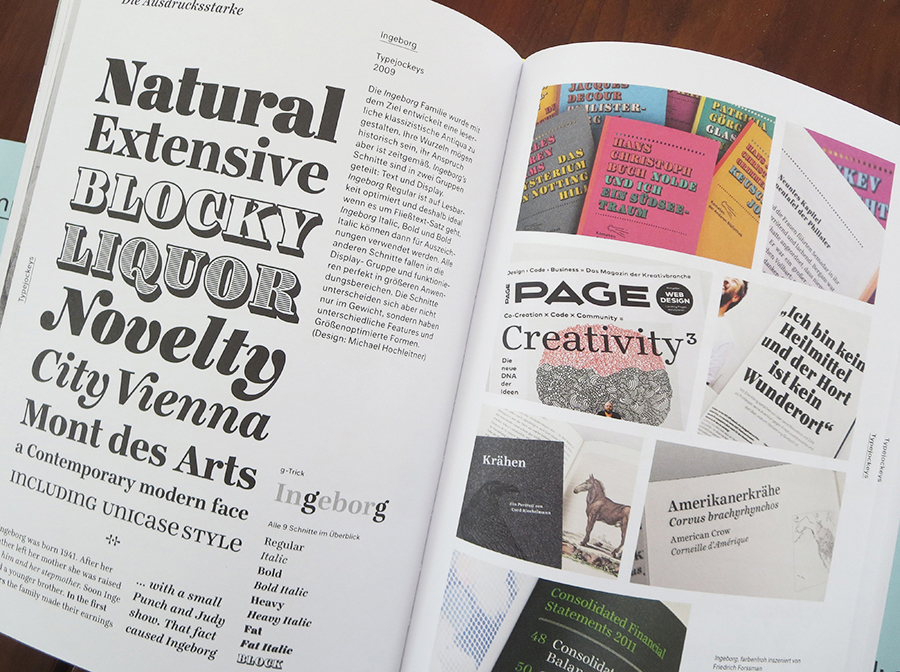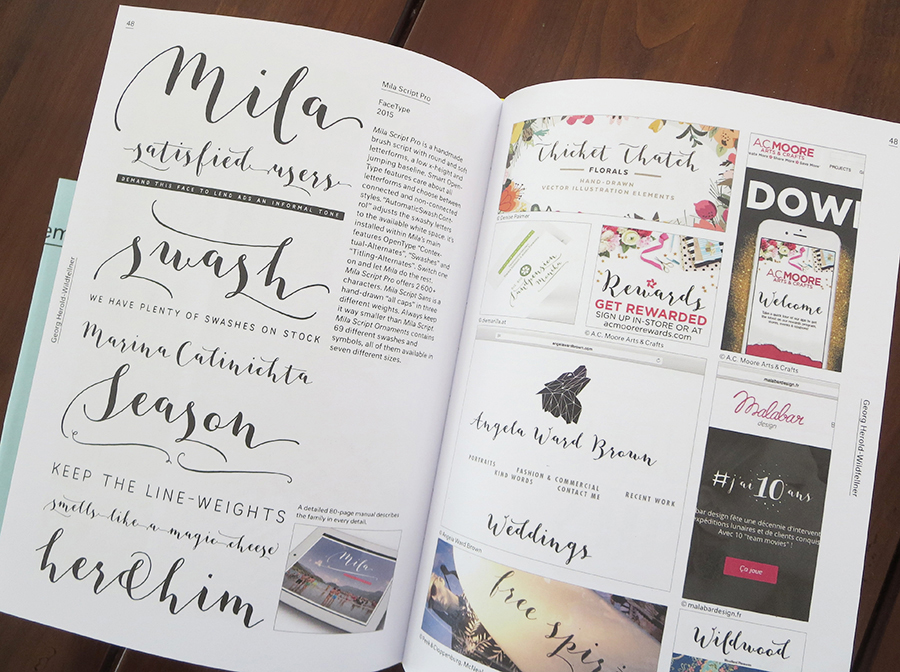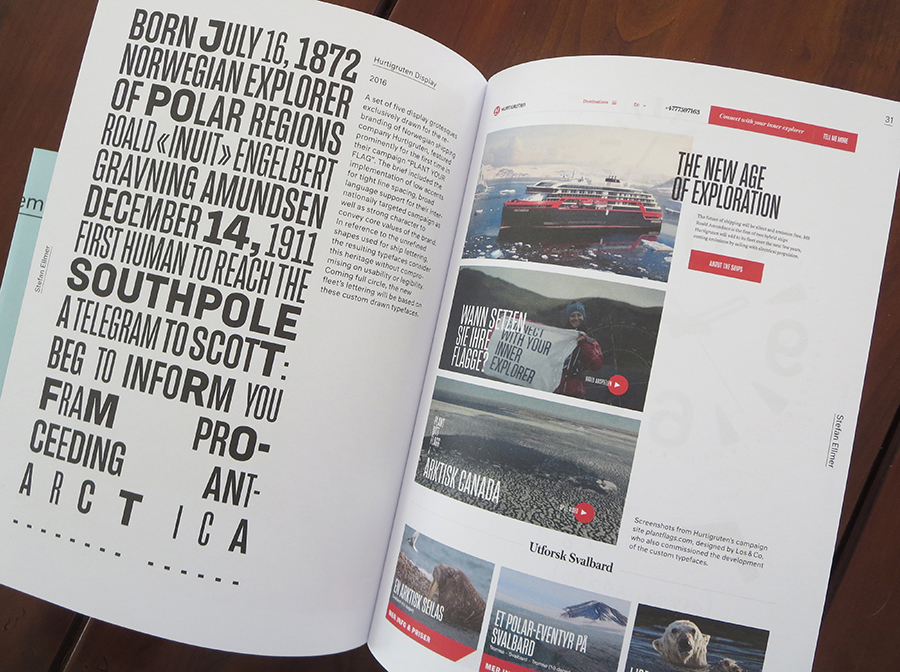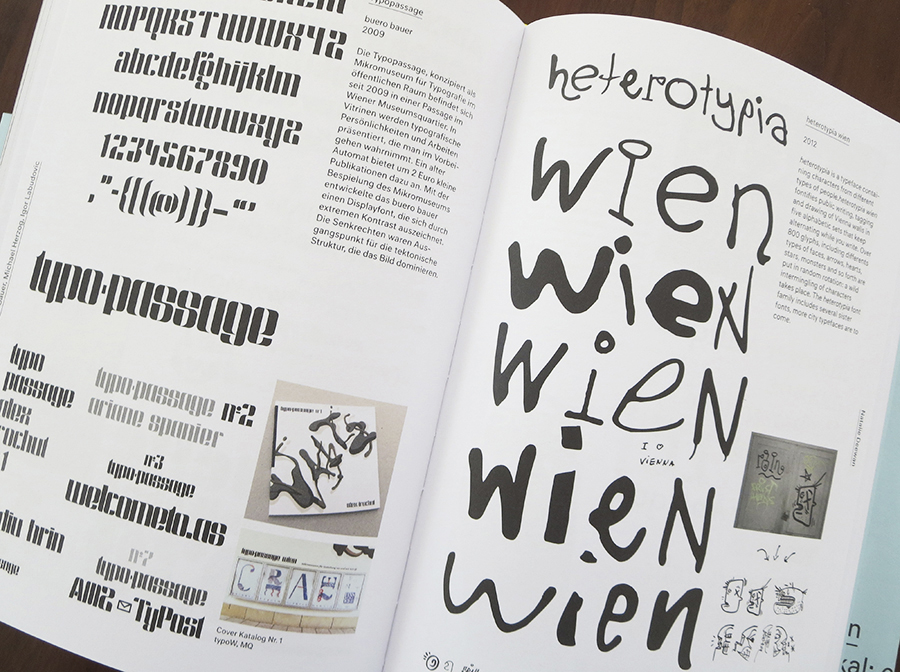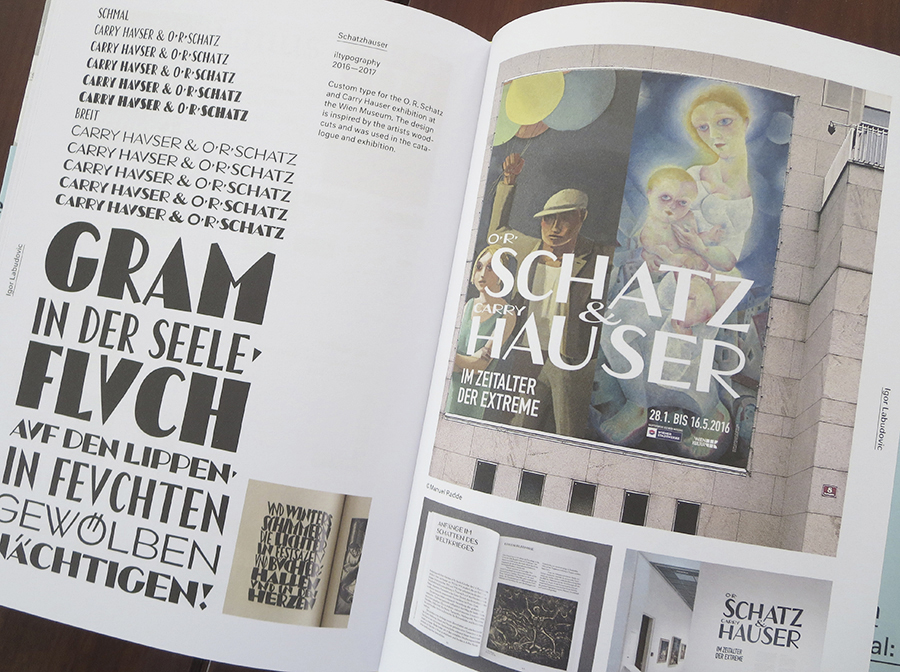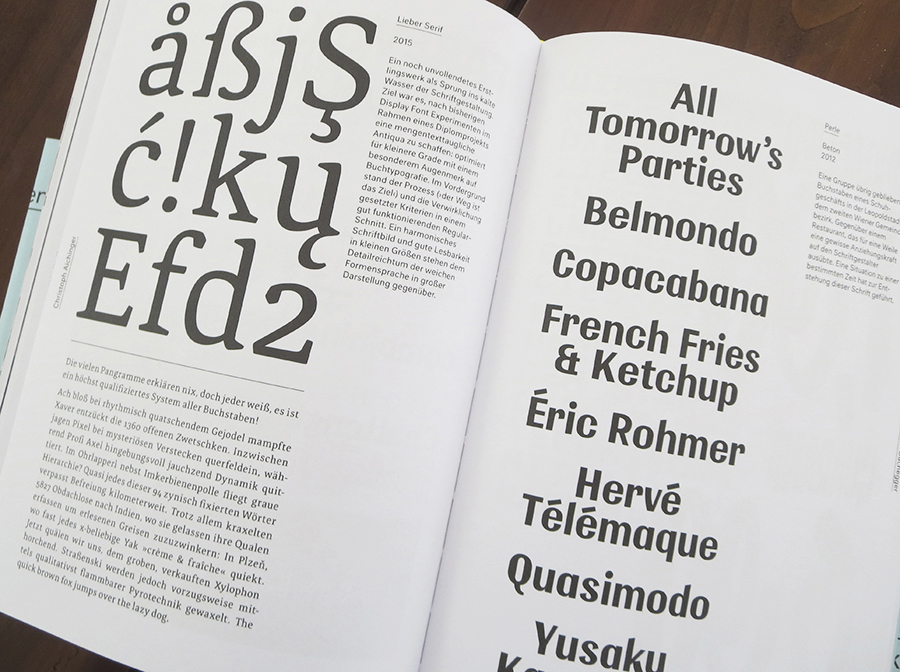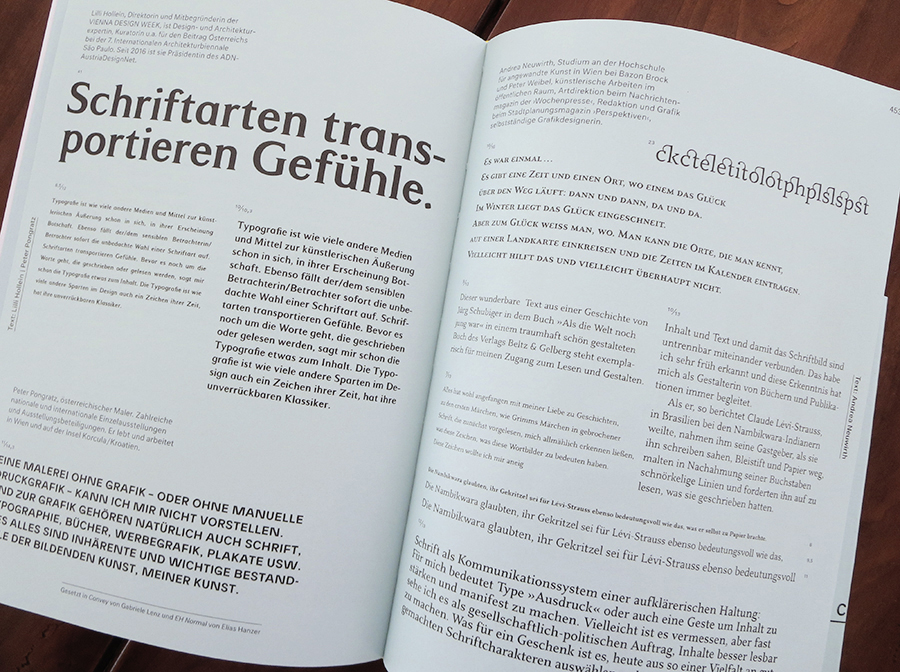
Typografie in Österreich – die Szene lebt. Buchempfehlung »Subtext: Typedesign«
Während dieser Zeit wurde die Typografie stark von gestalterischen Strömungen aus London beeinflusst und so bekam ich zwangsläufig Kontakt zu typografischen Formen, die bis dahin in Deutschland noch unbekannt waren. Heute pflege ich während meiner Besuche in Wien den Kontakt zu den Mitgliedern der Typografischen Gesellschaft Austria, tga. Deren Gründungsmitglieder Martin Tiefenthaler und Erich Monitzer haben im vergangenen Jahr gemeinsam mit Andreas Pawlik ein beachtliches Werk zu Typedesign mit starkem Österreichbezug herausgegeben: »Subtext: Typedesign«. Das Buch wird vom renommierten niggli-Verlag in der Schweiz publiziert.
Die Szene lebt
Österreich stand in der Vergangenheit nicht unbedingt für Schriftkunst. Jedoch hat das „… wunderbare Aufblühen der Schriftgestaltung längst auch in Österreich schönste Ergebnisse hervorgebracht“, so Friedrich Forssmann in einem Beitrag dieses Buches.
In der Tat: In dem Werk entdecke ich einige Fonts, die mir in bekannten Magazinen oder Consumer-Verpackungen schon öfter begegnet sind. Dabei ist es dann immer wieder ein spannendes Erlebnis, den jeweiligen Namen eines Fonts zu erfahren und aus welcher (österreichischen) Feder oder in welchem Büro dieser entstanden ist. Ebenso gefallen mir die Veröffentlichung nicht-publizierter Fonts und die zahlreichen Textbeiträge bekannter Autoren und Designer im Anhang, die einen historischen, zeitgenössischen und lokalen Bezug zu Typografie in Österreich vermitteln.
Das insgesamt 480 Seiten umfassende Werk ist sehr offen, illustrativ und informativ gestaltet und mit vielen Fontbeispielen und spannenden Anwendungsfotos versehen. Neben einer präzisen Beschreibung zur jeweiligen Vita der Designer und zur Entstehung eines Fonts bietet das Buch beispielsweise auch fotografische Einblicke in die Ateliers der Typedesigner. Ein spannendes Werk zum österreichischen Typedesign, das längst eine wichtige Position in der europäischen Kunst der Schriftgestaltung eingenommen hat.
»Subtext: Typedesign« ist anlässlich einer gleichnamigen Ausstellung erschienen. Das Buch archiviert Entwürfe von mehr als 50 lokal bis weltweit tätigen DesignerInnen und präsentiert auf über 450 Seiten gegenwärtige Schriftentwürfe mit nahem Österreichbezug und darüber hinaus. In einem umfassenden Textabschnitt, der weitere Anwendungen der Schriften zeigt, thematisieren renommierte AutorInnen aus unterschiedlichen Kultur- und Wissenschaftsbereichen ihr Verhältnis zu Schrift.“ Text: Niggli-Verlag.
Subtext: TypedesignZeitgenössich – Lokal: Contemporary – Austria
Andreas Pawlik, Martin Tiefenthaler (Hrsg.)